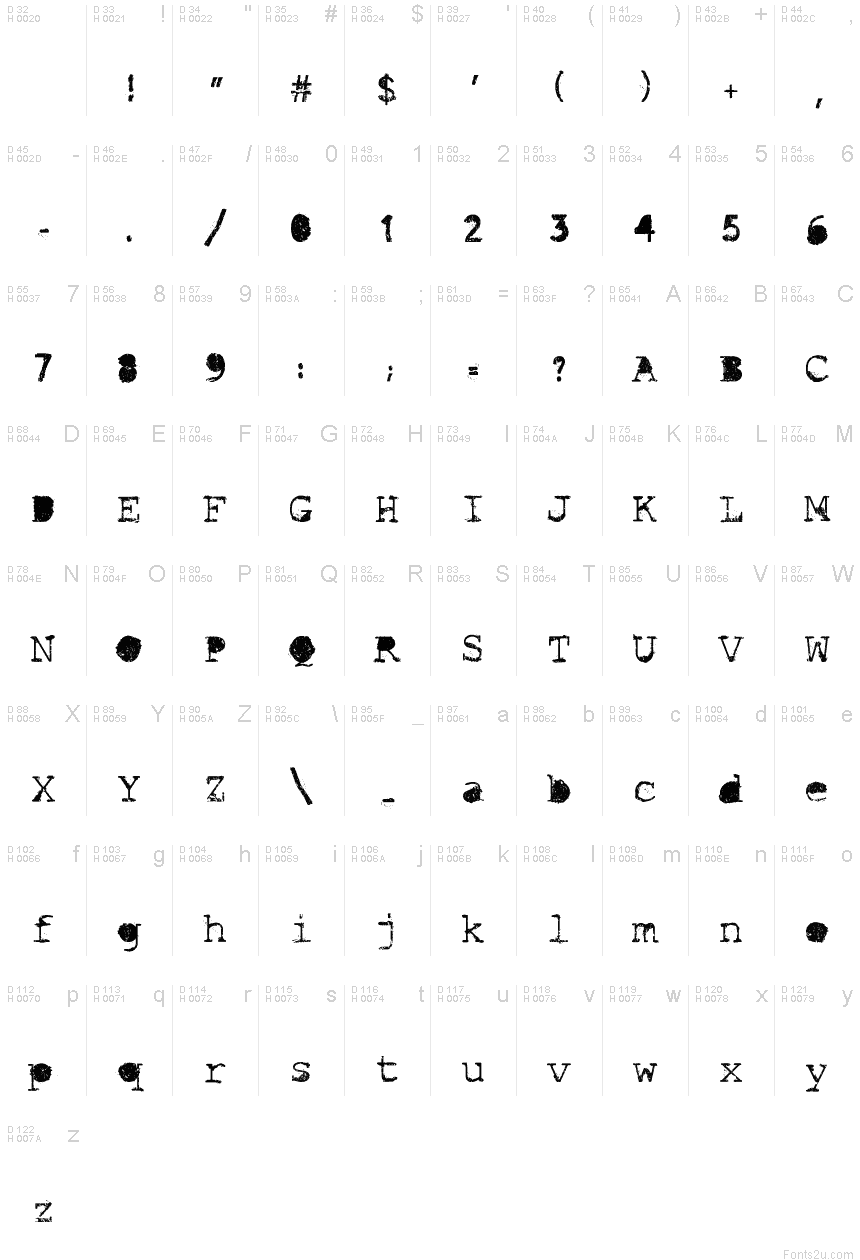
Idiot autorstwa Tommy'ego Cary'ego to darmowy, erodowany krój typu grunge, który wygląda, jakby został przeciągnięty przez kałużę atramentu, dziesięciokrotnie skserowany i porzucony na podłodze w klubowej piwnicy. Masywne litery rozpadają się na zadrapania, odpryski i luki, dzięki czemu każde słowo wydaje się głośne, surowe i nieco niestabilne. Ciasny, ciężki odstęp nadaje nagłówkom gęstą, klaustrofobiczną energię, która natychmiast przykuwa uwagę.
Wykorzystując Idiot, możesz nadać plakatom koncertowym, okładkom płyt punkowych lub metalowych, tytułom horrorów, undergroundowym zinom, grafikom streetwearowym czy sztuce protestu prawdziwie chaotyczny charakter. Ten darmowy font najlepiej sprawdza się w dużych rozmiarach, gdzie jego szorstka tekstura może w pełni wybrzmieć; połącz go z czystym, neutralnym bezszeryfem w tekstach głównych, aby brudny efekt uderzał z największą siłą.